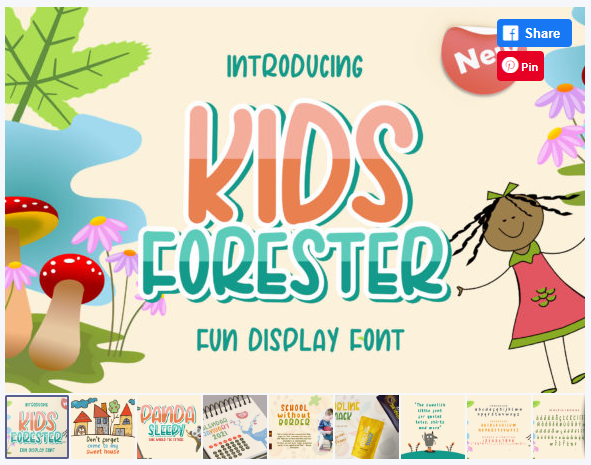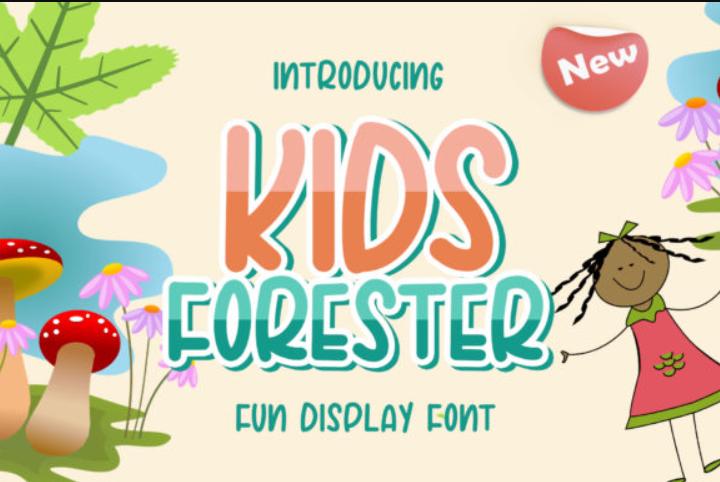
[Creativefabrica] Kids Forester Font (isolatype)
Kids Forester - милый, крутой и необычный рукописный шрифт. Независимо от темы, этот шрифт будет невероятно полезен для вашей библиотеки шрифтов, поскольку он может улучшить любое творение.